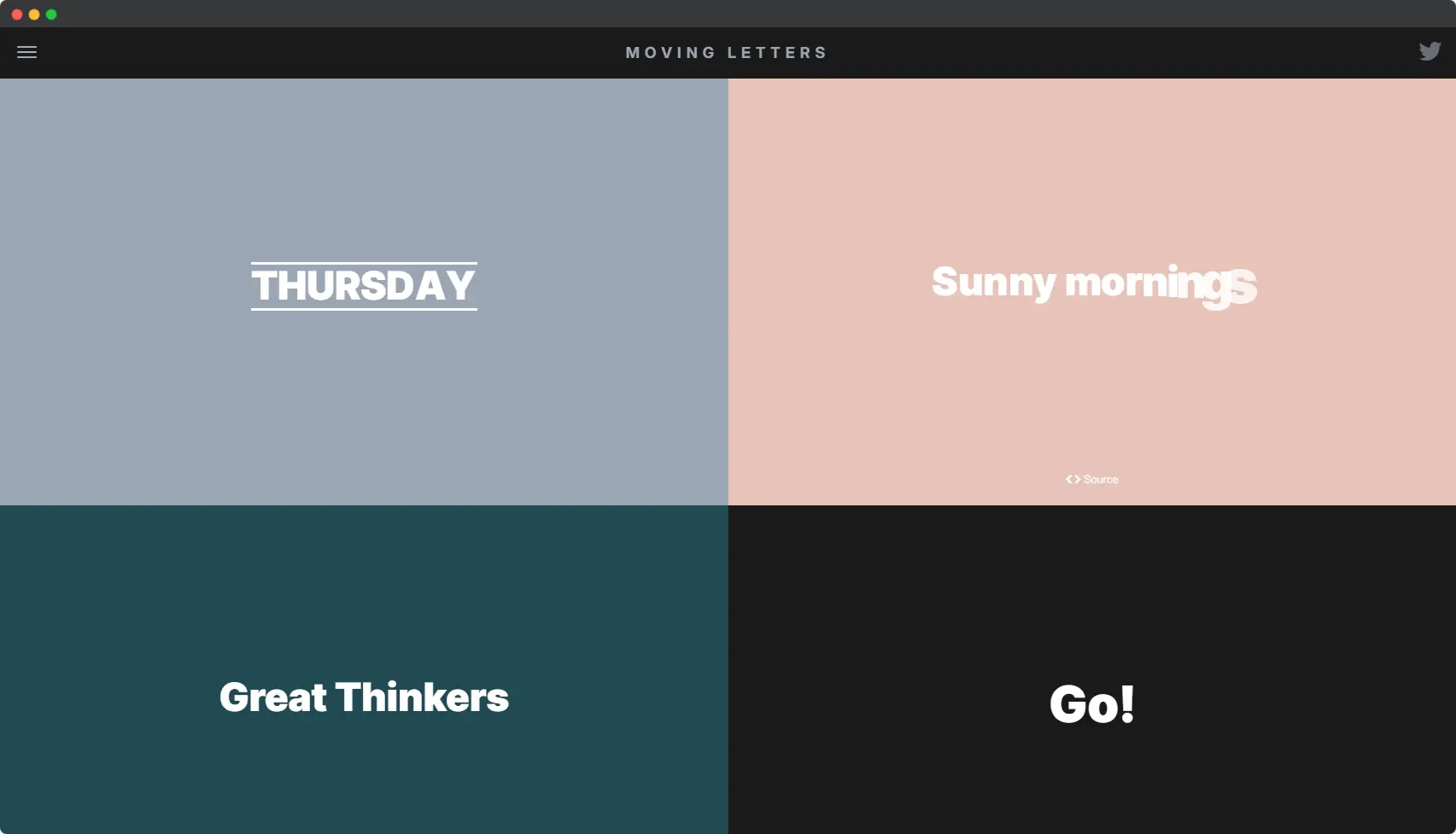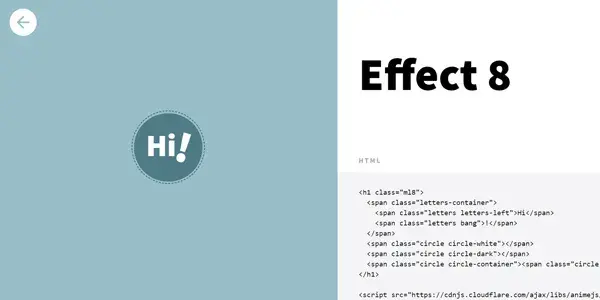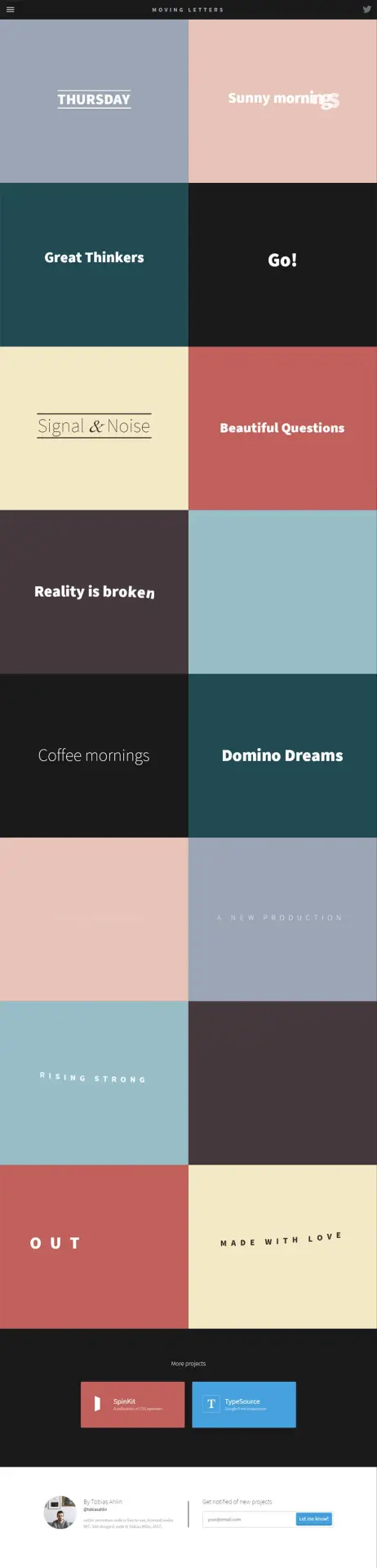
Dynamisez vos typographies web avec Moving Letters
Découvrez Moving Letters, la collection open-source d'animations qui va donner vie à vos textes ! Avec ces 16 effets typographiques uniques, vous pourrez facilement ajouter une touche ludique et expressive à vos projets web.
Pourquoi ajouter des animations aux textes d'un site web ?
Ajouter des animations aux textes d'un site web peut offrir plusieurs avantages significatifs, tant d'un point de vue esthétique que fonctionnel.
1. Rendre le site plus attrayant visuellement
Un design dynamique et interactif attire l'attention des visiteurs et les encourage à explorer davantage le contenu proposé. Par exemple, des effets tels que le déplacement ou le changement de couleur du texte lorsqu'on passe la souris dessus peuvent rendre la navigation plus ludique et engageante.
2. Améliorer l'expérience utilisateur en facilitant la compréhension et la navigation
Les animations peuvent être utilisées pour indiquer des actions ou des transitions importantes, comme le chargement d'une nouvelle page, la soumission d'un formulaire ou la mise en avant de certaines informations clés. En guidant subtilement les utilisateurs à travers le site, les animations peuvent réduire la confusion et rendre l'interaction plus intuitive.
3. Contribuer à renforcer l'identité de la marque
Un style d'animation cohérent et bien conçu peut refléter les valeurs et la personnalité de l'entreprise, créant ainsi une expérience mémorable pour les visiteurs. Que ce soit par des transitions fluides, des effets de survol ou des introductions animées, le bon usage des animations peut faire une grande différence dans la perception globale du site web et, par conséquent, dans la fidélisation des utilisateurs.
Animez vos textes en JavaScript avec Moving Letters
Découvrez Moving Letters, une collection open-source d'animations prêtes à l'emploi pour tous les navigateurs, idéale pour donner une touche ludique et expressive à vos projets web.
Comme nous l'avons expliqué précédement, ces animations sont parfaites pour mettre en valeur des textes, que ce soit sur les pages d'accueil ou pour attirer l'attention sur des éléments clés.
Ces exemples vous donnent un aperçu des différentes techniques pour animer des textes en JavaScript. Vous pouvez les adapter et les combiner selon vos besoins pour créer des animations uniques sur votre site web.
N'oubliez pas que les animations doivent être utilisées avec modération pour ne pas nuire à l'expérience utilisateur et à l'accessibilité de votre site. Il est également recommandé d'utiliser des bibliothèques d'animation JavaScript populaires comme GreenSock (GSAP) ou Animate.css pour des animations plus complexes et performantes.